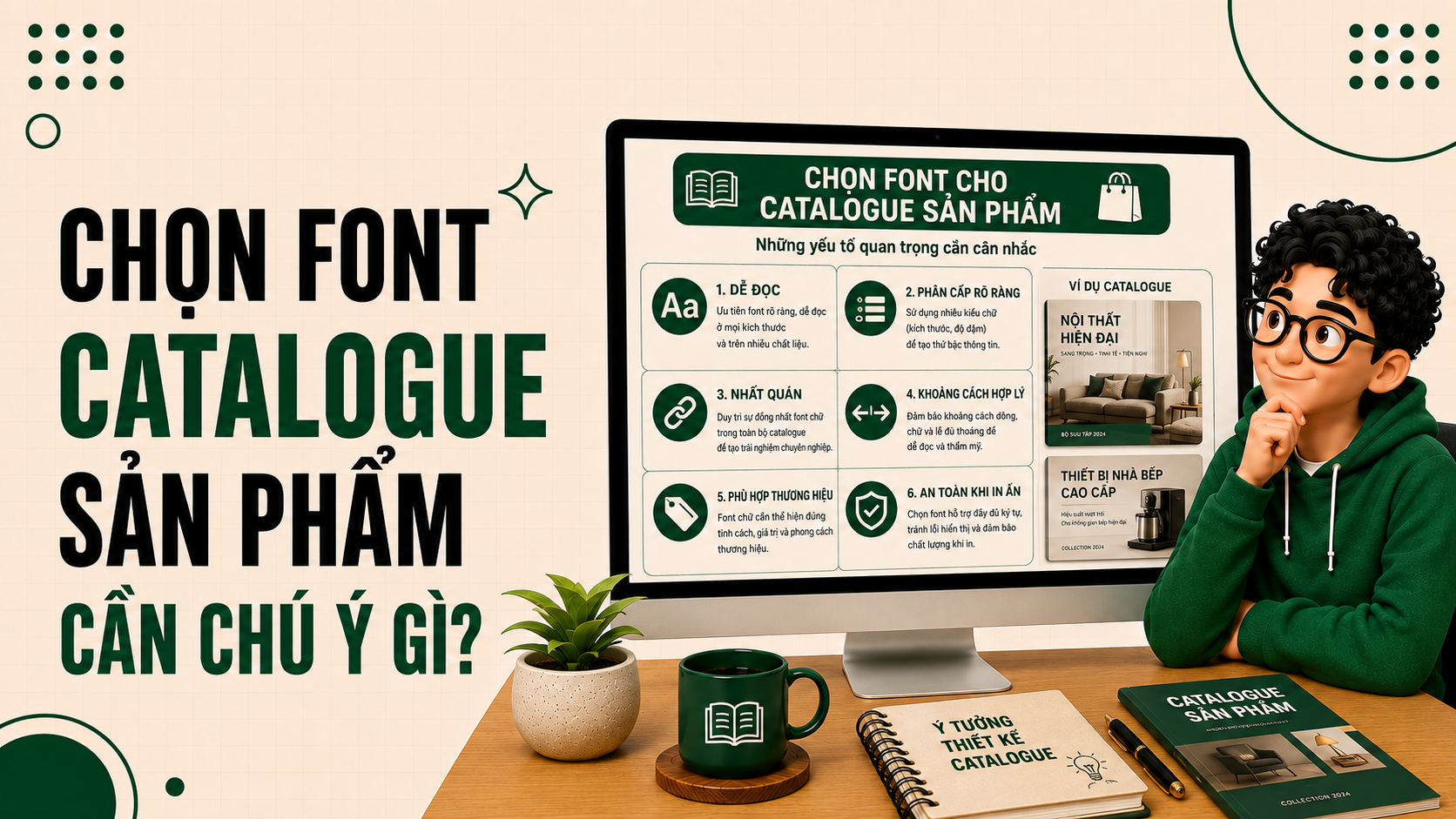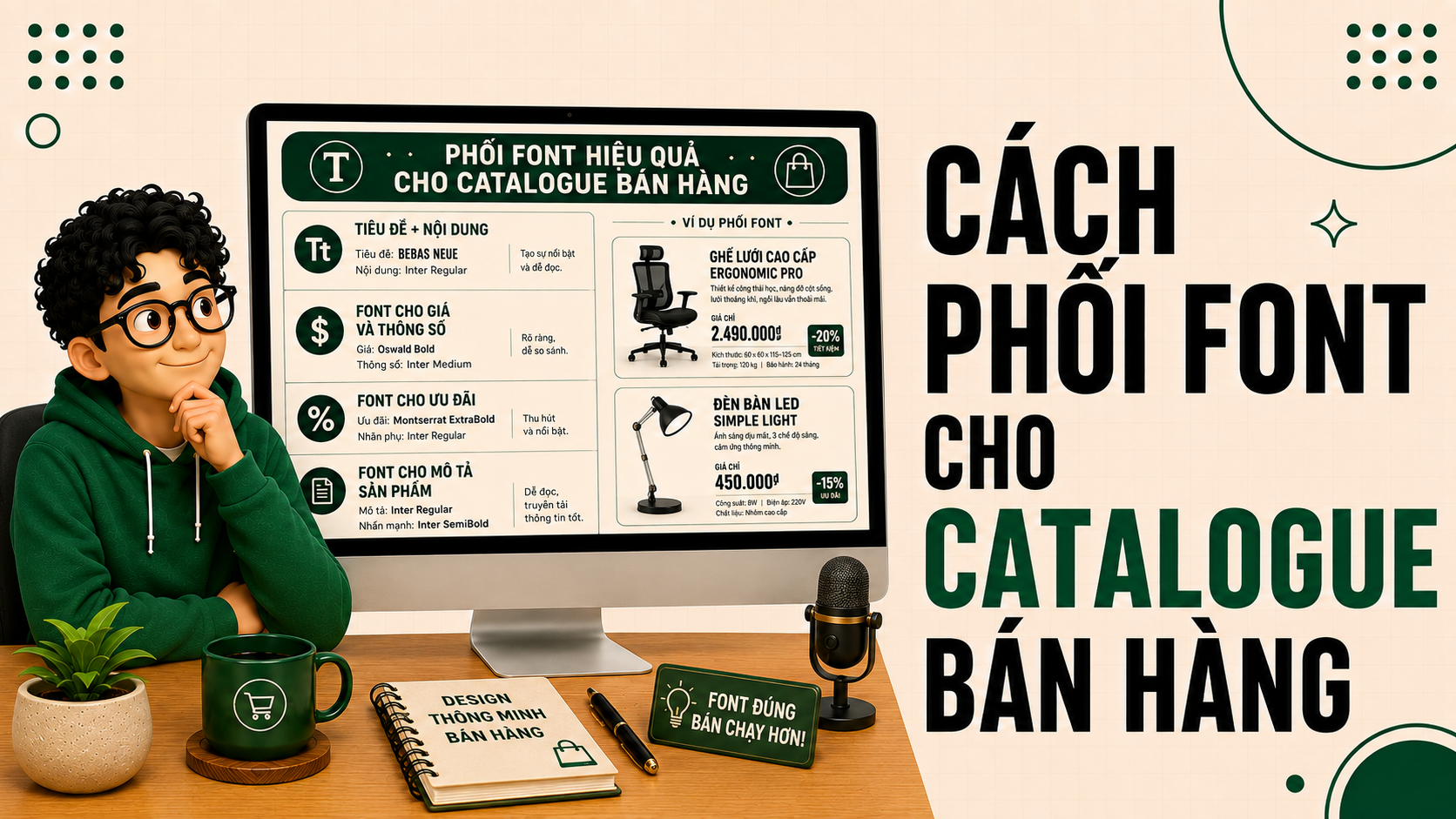
Top 20 font chữ cho catalogue sản phẩm, sales kit và tài liệu bán hàng
Gợi ý 20 font TH Việt hóa cho catalogue sản phẩm, sales kit, brochure sản phẩm, profile sản phẩm và tài liệu bán hàng.
Catalogue sản phẩm, sales kit và tài liệu bán hàng là những ấn phẩm phải làm cùng lúc nhiều việc: giới thiệu thương hiệu, trình bày sản phẩm, giải thích lợi ích, so sánh thông số, dẫn dắt khách hàng đến bước mua hoặc liên hệ. Vì vậy, font chữ trong catalogue không chỉ cần đẹp mà còn phải giúp người đọc quét thông tin nhanh, hiểu cấu trúc rõ và cảm thấy sản phẩm đáng tin.
Bài viết này gợi ý 20 font TH Việt hóa phù hợp cho catalogue sản phẩm, sales kit, brochure sản phẩm, profile sản phẩm và tài liệu bán hàng. Danh sách được chia tự nhiên giữa nhóm sans-serif dễ đọc cho bảng thông số, nhóm serif sang cho bìa/collection, và nhóm font thương hiệu để tạo điểm nhấn ở trang sản phẩm chủ lực.
Chọn font catalogue sản phẩm cần chú ý gì?
Một catalogue thường có nhiều cấp chữ: tên sản phẩm, mô tả ngắn, thông số, giá, mã SKU, lợi ích, chú thích ảnh, lời chứng thực và CTA. Nếu dùng một font quá cầu kỳ cho tất cả, tài liệu sẽ nhanh rối. Cách an toàn là chọn một font body rõ, một font title có cá tính và một style nhấn cho giá hoặc thông điệp bán hàng. Với catalogue dài, sự nhất quán quan trọng hơn việc thay nhiều font cho đẹp mắt.
Top 20 font TH cho catalogue, sales kit và tài liệu bán hàng
1. TH Legacy Sans - catalogue nhiều sản phẩm, bảng thông số, mô tả tính năng và sales kit B2B
Tải font TH Legacy Sans nếu anh đang thiết kế catalogue nhiều sản phẩm, bảng thông số, mô tả tính năng và sales kit B2B. Điểm mạnh của TH Legacy Sans là sạch, trung tính, giúp thông tin sản phẩm dễ đọc ngay cả khi catalogue có nhiều trang. Khi đưa vào catalogue, hãy test font trên một trang sản phẩm thật gồm tên sản phẩm, ảnh, mô tả ngắn, thông số, giá và CTA.
Với TH Legacy Sans, anh nên giữ phân cấp chữ rõ ràng: title lớn cho tên sản phẩm hoặc collection, heading vừa cho lợi ích, body nhỏ cho mô tả, và label gọn cho thông số. Nếu font được dùng cho bìa hoặc headline, phần bảng giá và mô tả nên dùng một sans-serif dễ đọc hơn để tài liệu không bị nặng mắt.
2. TH Guton - sales kit có nhiều cấp nội dung, profile sản phẩm và brochure dịch vụ
Tải font TH Guton nếu anh đang thiết kế sales kit có nhiều cấp nội dung, profile sản phẩm và brochure dịch vụ. Điểm mạnh của TH Guton là có nhiều style nên rất tiện để phân cấp tên sản phẩm, headline, bullet và giá. Khi đưa vào catalogue, hãy test font trên một trang sản phẩm thật gồm tên sản phẩm, ảnh, mô tả ngắn, thông số, giá và CTA.
Với TH Guton, anh nên giữ phân cấp chữ rõ ràng: title lớn cho tên sản phẩm hoặc collection, heading vừa cho lợi ích, body nhỏ cho mô tả, và label gọn cho thông số. Nếu font được dùng cho bìa hoặc headline, phần bảng giá và mô tả nên dùng một sans-serif dễ đọc hơn để tài liệu không bị nặng mắt.
3. TH Manisans - catalogue cao cấp, proposal sản phẩm và tài liệu chào hàng cho khách doanh nghiệp
Tải font TH Manisans nếu anh đang thiết kế catalogue cao cấp, proposal sản phẩm và tài liệu chào hàng cho khách doanh nghiệp. Điểm mạnh của TH Manisans là hiện đại, sang vừa phải, tạo cảm giác thương hiệu được đầu tư chỉn chu. Khi đưa vào catalogue, hãy test font trên một trang sản phẩm thật gồm tên sản phẩm, ảnh, mô tả ngắn, thông số, giá và CTA.
Với TH Manisans, anh nên giữ phân cấp chữ rõ ràng: title lớn cho tên sản phẩm hoặc collection, heading vừa cho lợi ích, body nhỏ cho mô tả, và label gọn cho thông số. Nếu font được dùng cho bìa hoặc headline, phần bảng giá và mô tả nên dùng một sans-serif dễ đọc hơn để tài liệu không bị nặng mắt.
4. TH Cameo Sans - catalogue lifestyle, mỹ phẩm, giáo dục, dịch vụ và sản phẩm tiêu dùng
Tải font TH Cameo Sans nếu anh đang thiết kế catalogue lifestyle, mỹ phẩm, giáo dục, dịch vụ và sản phẩm tiêu dùng. Điểm mạnh của TH Cameo Sans là thanh lịch, dễ tiếp cận, không làm tài liệu bán hàng bị quá lạnh. Khi đưa vào catalogue, hãy test font trên một trang sản phẩm thật gồm tên sản phẩm, ảnh, mô tả ngắn, thông số, giá và CTA.
Với TH Cameo Sans, anh nên giữ phân cấp chữ rõ ràng: title lớn cho tên sản phẩm hoặc collection, heading vừa cho lợi ích, body nhỏ cho mô tả, và label gọn cho thông số. Nếu font được dùng cho bìa hoặc headline, phần bảng giá và mô tả nên dùng một sans-serif dễ đọc hơn để tài liệu không bị nặng mắt.
5. TH Artega - catalogue tối giản, lookbook sản phẩm, sales deck startup và tài liệu công nghệ
Tải font TH Artega nếu anh đang thiết kế catalogue tối giản, lookbook sản phẩm, sales deck startup và tài liệu công nghệ. Điểm mạnh của TH Artega là gọn, hiện đại, hợp với bố cục nhiều khoảng trắng và ảnh sản phẩm lớn. Khi đưa vào catalogue, hãy test font trên một trang sản phẩm thật gồm tên sản phẩm, ảnh, mô tả ngắn, thông số, giá và CTA.
Với TH Artega, anh nên giữ phân cấp chữ rõ ràng: title lớn cho tên sản phẩm hoặc collection, heading vừa cho lợi ích, body nhỏ cho mô tả, và label gọn cho thông số. Nếu font được dùng cho bìa hoặc headline, phần bảng giá và mô tả nên dùng một sans-serif dễ đọc hơn để tài liệu không bị nặng mắt.
Với 20 font TH Việt hóa trên, anh có thể xây sales kit theo nhiều phong cách: tối giản, sang trọng, kỹ thuật, lifestyle, boutique hoặc B2B cao cấp. Chọn đúng font, giữ phân cấp rõ và kiểm tra trên bản PDF/mobile sẽ giúp catalogue bán hàng có sức thuyết phục hơn rất nhiều.